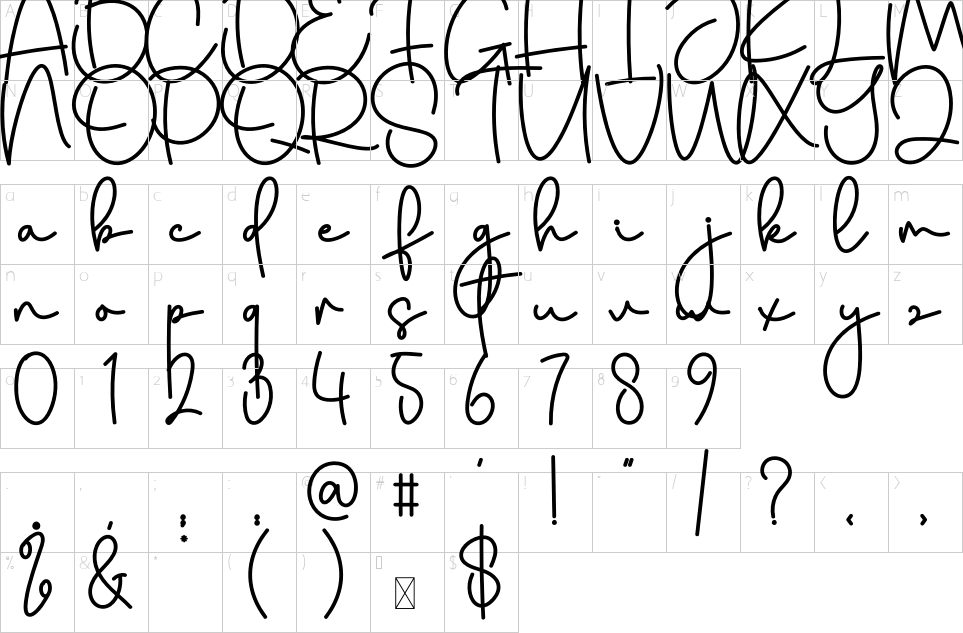
Descubra a fonte grátis ‘Daddy Font’ para Windows e Mac. Esta elegante e minimalista fonte foi criada pelo designer scratchones e tem sido baixada 252 vezes. Se você está procurando por uma fonte que se destaca no seu design sem comprometer a simplicidade, essa pode ser a escolha perfeita para você. Com sua linhas leves e harmoniosas, a Daddy Font é ideal tanto para títulos quanto para subtítulos e texto corrido. Não perca tempo; está aqui uma fonte elegante que se adapta à sua necessidade de design sem precisar gastar dinheiro extra.